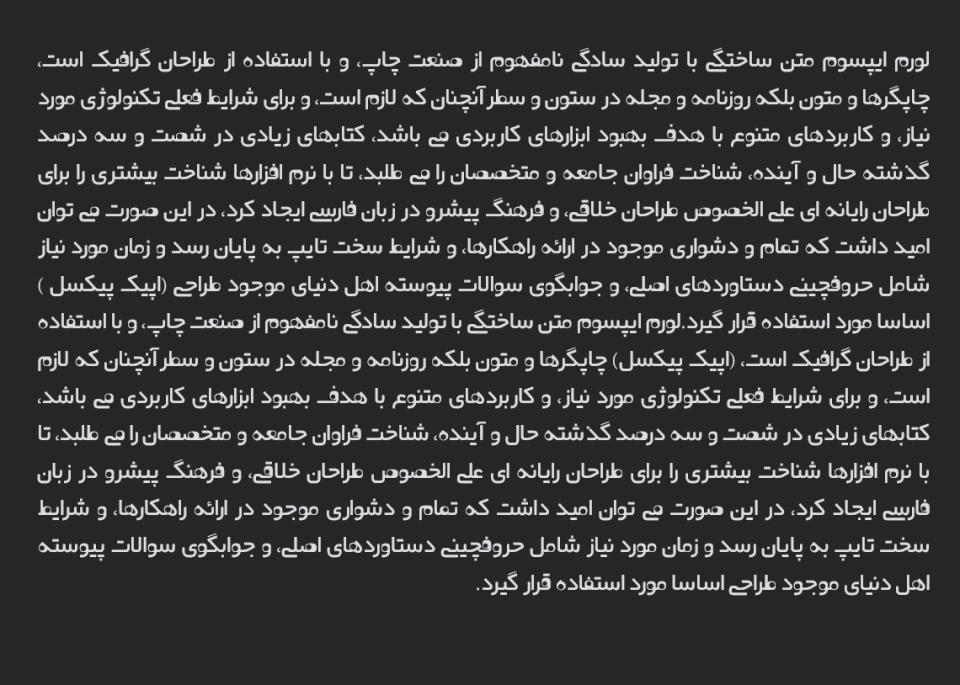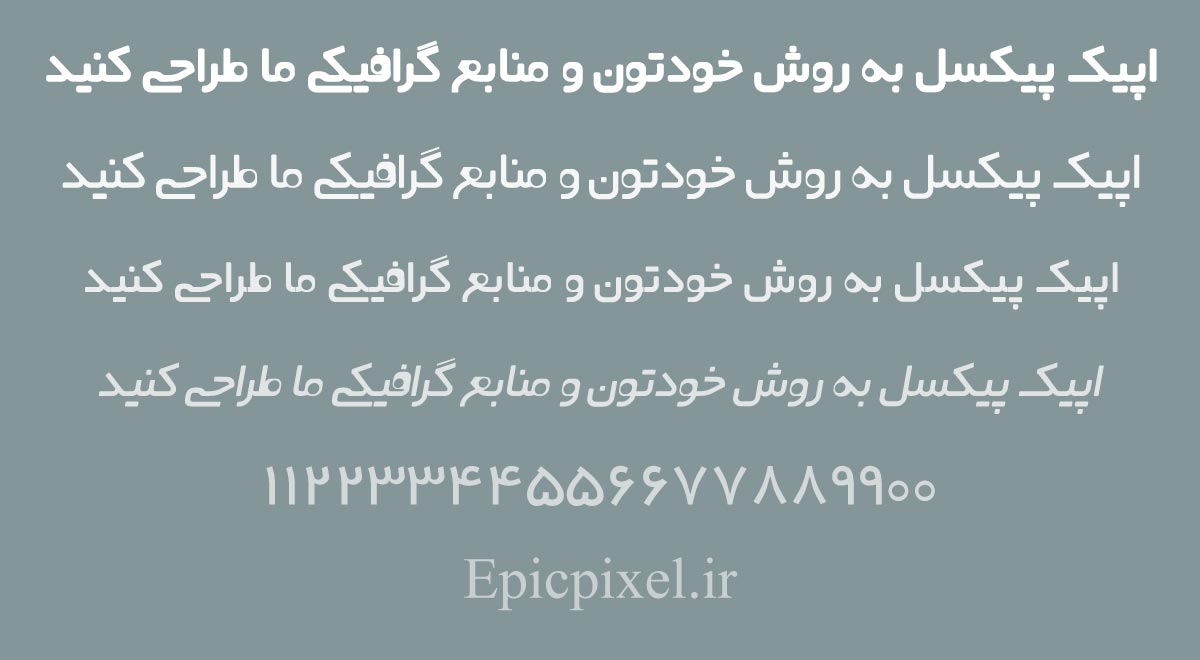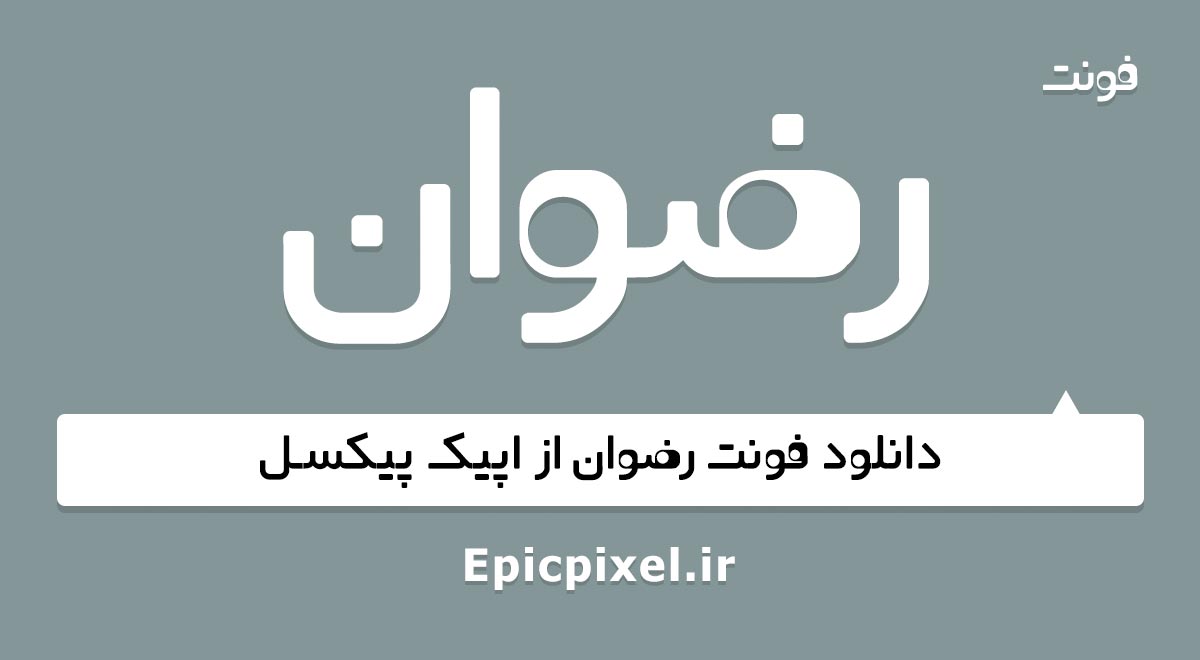
فونت رضوان، با طراحی خاص و منحصربه فردش، گزینه ای ایده آل برای طراحانی است که به دنبال جلوه ای مدرن و در عین حال خوانا در آثار خود هستند. این فونت، با داشتن اعراب و پشتیبانی کامل از حروف فارسی و عربی، خیال شما را از بابت نمایش صحیح متون در هر اندازه ای راحت می کند.
یکی از ویژگی های برجسته فونت رضوان، کنترل دقیق فاصله بین حروف است که به خوانایی بیشتر متن کمک شایانی می کند. همچنین، وجود ده ها حرف ترکیبی در این فونت، دست طراحان را برای خلق آثار خلاقانه تر باز می گذارد. این ویژگی به ویژه در طراحی لوگوتایپ و عناوین جذاب بسیار کاربردی است.
اگرچه فونت رضوان در بیشتر نرم افزارها به خوبی عمل می کند، اما ممکن است در نرم افزار فتوشاپ برای نمایش صحیح حروف ترکیبی، نیاز به فعال کردن گزینه Ligatures در تنظیمات متن باشد. این نکته ای است که باید در هنگام استفاده از این فونت در فتوشاپ به آن توجه داشت. در کل، فونت رضوان با حجم مناسب و دو وزن مختلف (پر و نرمال)، ابزاری کارآمد و رایگان برای طراحان گرافیک و وب به شمار می رود و به دلیل ویژگی های ذکر شده و رایگان بودنش ارزش دانلود را دارد.